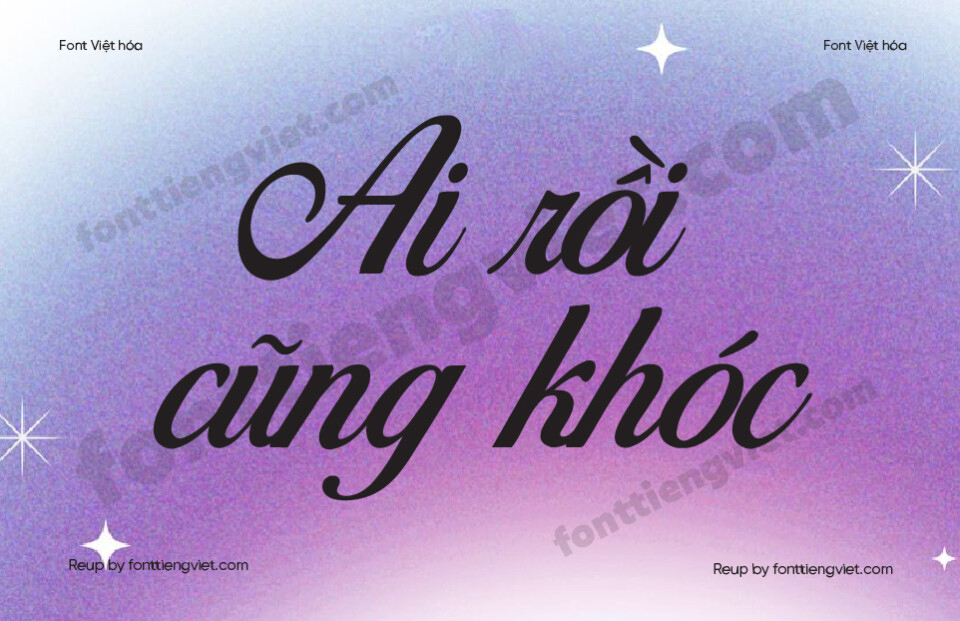
Font Việt hóa UTM Birds Paradise: Tuyệt Tác Font Chữ Viết Tay Bay Bổng
Nếu bạn đang tìm kiếm một bộ font chữ mang phong cách nghệ thuật, mềm mại và đầy sự phóng khoáng cho các thiết kế của mình, thì Font Việt hóa UTM Birds Paradise chính là lựa chọn không thể bỏ qua. Đây là một trong những font chữ script được ưa chuộng nhất trong cộng đồng thiết kế Việt Nam nhờ những đường nét thanh mảnh nhưng vô cùng tinh tế.
Tổng quan về Font UTM Birds Paradise
UTM Birds Paradise là bộ font được Việt hóa từ phiên bản gốc bởi đội ngũ UTM. Đúng như tên gọi “Thiên đường của những loài chim”, font chữ này gợi lên cảm giác tự do, nhẹ nhàng và đầy lãng mạn.
Đặc điểm nổi bật của font chữ
Đường nét uyển chuyển: Các ký tự được thiết kế với độ nghiêng vừa phải, tạo cảm giác như những nét vẽ tay thủ công tỉ mỉ.
Hỗ trợ tiếng Việt hoàn hảo: Đã được tinh chỉnh các dấu câu (huyền, sắc, hỏi, ngã, nặng) sao cho cân đối, không bị lỗi hiển thị hay nhảy chữ khi gõ trong Photoshop, Illustrator hay Canva.
Tính ứng dụng cao: Dễ dàng kết hợp với các font chữ không chân (Sans Serif) hiện đại để tạo ra sự tương phản ấn tượng.
Ứng dụng của UTM Birds Paradise trong thiết kế
Nhờ vẻ đẹp bay bổng và sang trọng, UTM Birds Paradise thường xuyên xuất hiện trong các dự án sáng tạo đòi hỏi tính thẩm mỹ cao:
Thiết kế thiệp cưới: Tạo nên sự lãng mạn, ngọt ngào cho lời mời và tên cô dâu chú rể.
Branding & Logo: Phù hợp cho các thương hiệu về mỹ phẩm, thời trang, spa hoặc các sản phẩm handmade.
Quotes & Typography: Những câu trích dẫn về tình yêu, cuộc sống sẽ trở nên truyền cảm hứng hơn rất nhiều khi sử dụng bộ font này.
Bìa sách & Tạp chí: Mang lại vẻ ngoài nghệ thuật và lôi cuốn người xem ngay từ cái nhìn đầu tiên.
Lưu ý khi sử dụng Font Việt hóa UTM Birds Paradise
Mặc dù là một font chữ tuyệt đẹp, nhưng để đạt được hiệu quả thị giác tốt nhất, bạn nên lưu ý một số điểm sau:
Tránh viết hoa toàn bộ: Đối với các dòng font Script như UTM Birds Paradise, việc viết hoa tất cả các chữ cái sẽ làm rối mắt và rất khó đọc. Hãy chỉ viết hoa chữ cái đầu tiên của từ.
Khoảng cách dòng (Leading): Do có các đường nét móc lên và kéo xuống khá dài, bạn cần điều chỉnh khoảng cách dòng hợp lý để các ký tự không bị đè lên nhau.
Bối cảnh sử dụng: Font này phù hợp nhất với phong cách Vintage, Elegant hoặc Feminine.
Kết luận: UTM Birds Paradise không chỉ là một phông chữ, mà là một công cụ giúp bạn truyền tải cảm xúc vào từng con chữ. Đừng ngần ngại bổ sung ngay bộ font Việt hóa cực phẩm này vào kho tài nguyên thiết kế của mình.